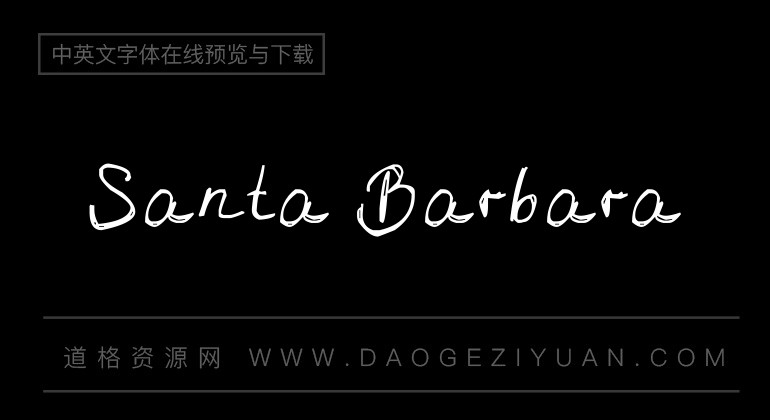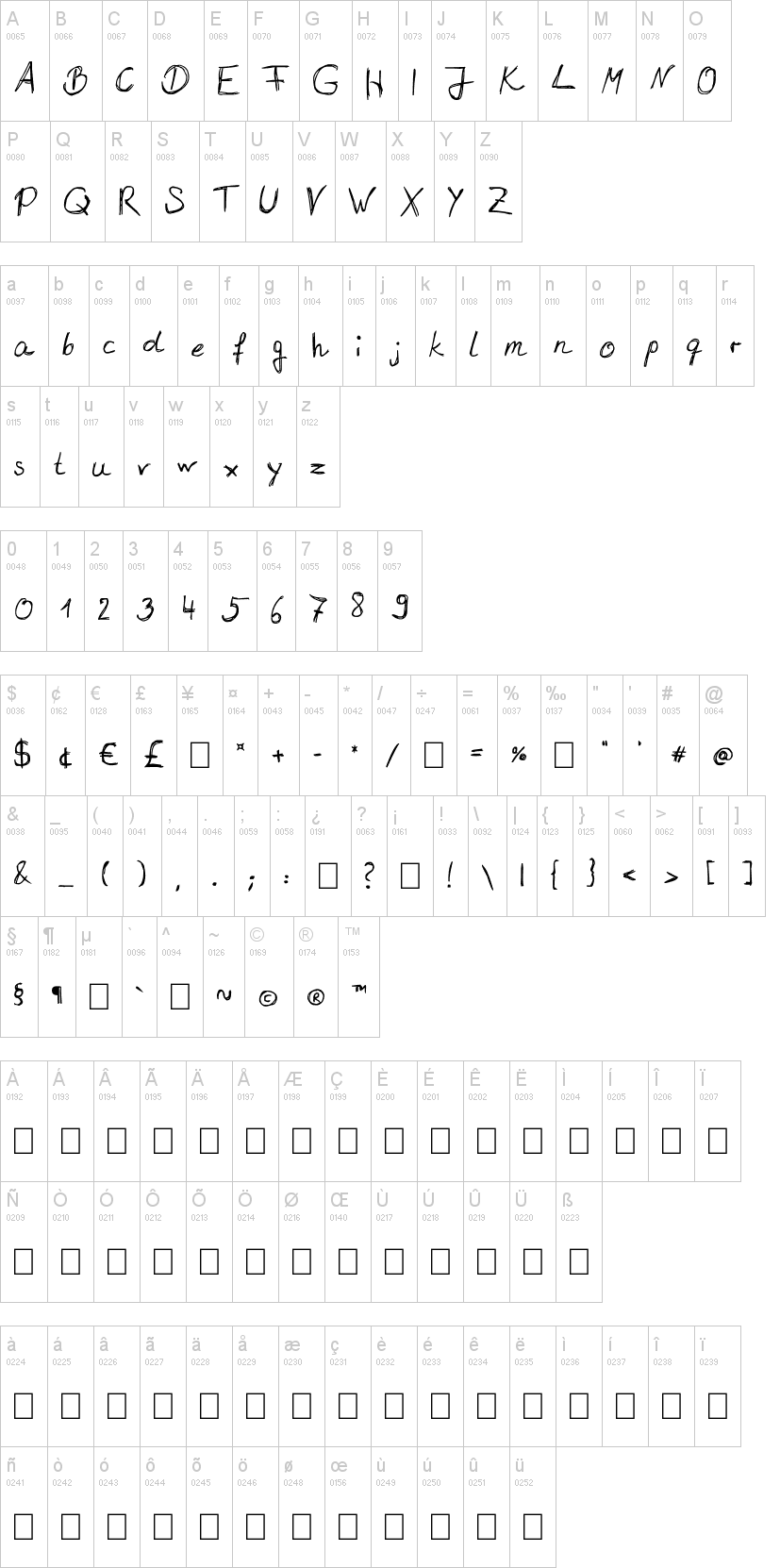
Santa Barbara 字体是一款英文草书字体,由著名的英国字体设计师John Stracke于1987年创作,受到18世纪西班牙书法的启发。它的设计灵感来自西班牙老城市圣塔芭芭拉(Santa Barbara)的建筑和历史文化。它的字形充满了浓郁的西班牙气息,具有流畅的线条,温柔的曲线,给人以温暖的感觉。Santa Barbara字体适用于印刷品、网页设计、图标设计等多种应用场景。内容介绍
Santa Barbara是一款非常不错的手写艺术字体,具有很好的视觉感,适合于文化类的宣传设计、商业类品牌的广告和产品包装设计以及个性化文字排版等较多场景。